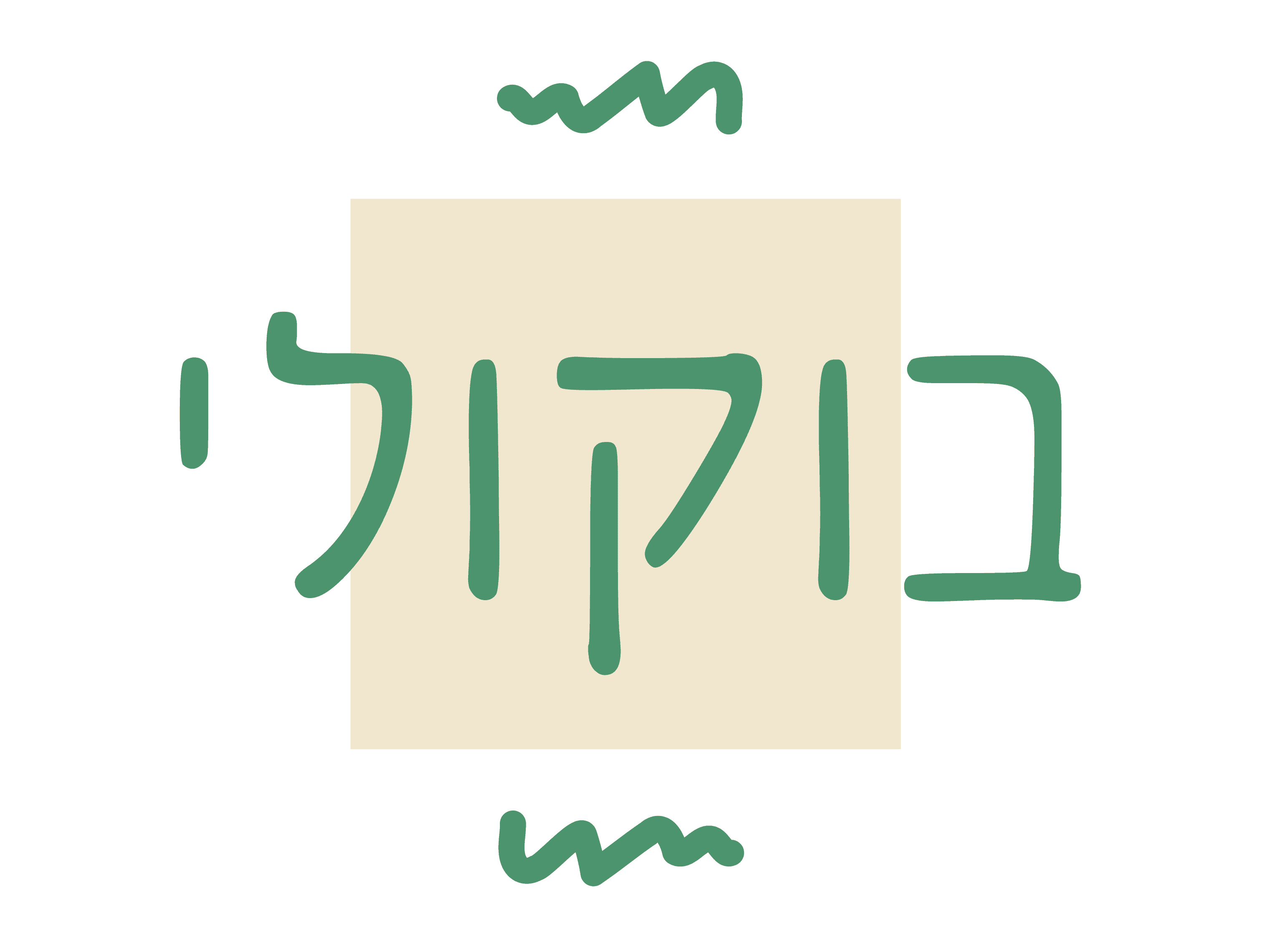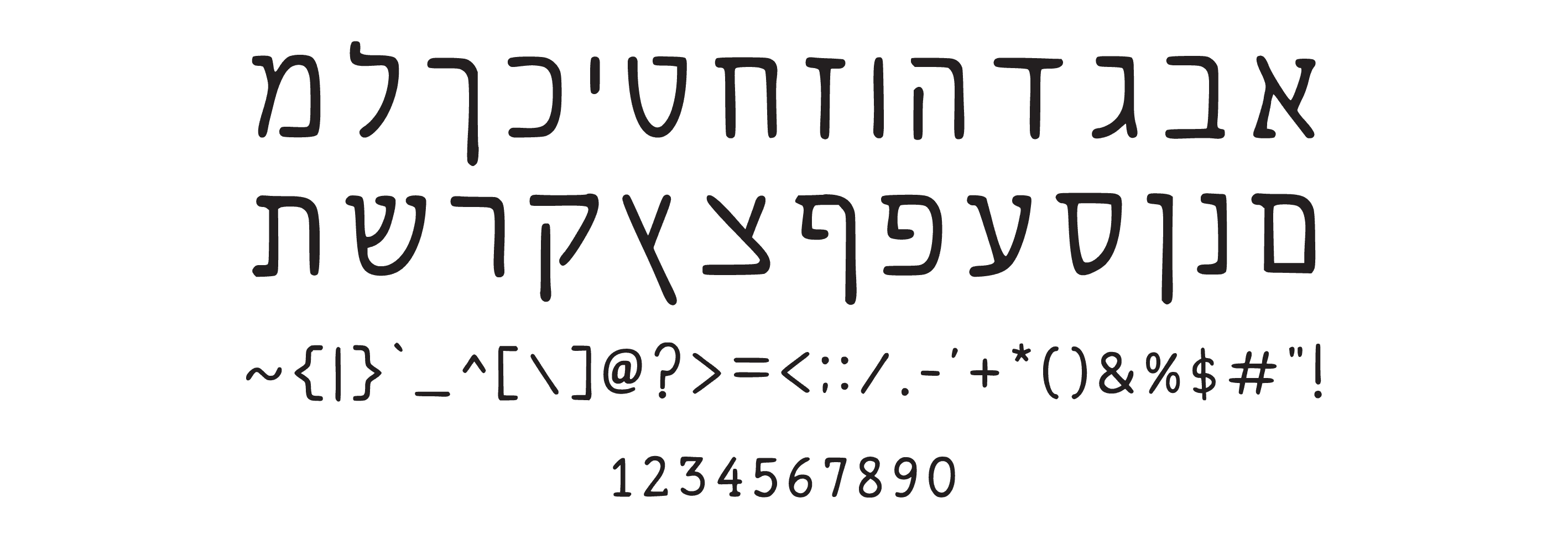
פונט בוקולי
פונט עברי טבעי וקליל בסגנון כתב יד, מתאים לעיצובים חמים, טבעיים ואישיים.
בוקולי — פונט עם לב רחב ואותיות עגולות
בוקולי הוא בדיוק הפונט שמחבק אותך ברגע שמביטים בו.
הוא קליל, רך ומלא באווירה חמה ונעימה, כאילו נכתב ביד רגועה בעיפרון או עט.
הפונט הזה מדמה כתב יד אורגני, עם קווים חופשיים ומלאי חיים, ויוצר תחושה אישית, כפרית ומזמינה.
הוא מושלם לכל עיצוב שרוצה לדבר בגובה העיניים — בעדינות, ברוך, ובכנות.
איפה הוא מרגיש בבית?
🍃 עיצובי טבע, קיימות ואקולוגיה
🍃 ברכות ידניות ואישיות
🍃 פוסטרים חמודים וביתיים
🍃 עיצובי ילדים ומשפחות
למי הוא מתאים?
לכל מי שמחפש פונט אישי, אנושי, רך ונעים לעין, כזה שנראה כאילו נכתב במיוחד עבורך.